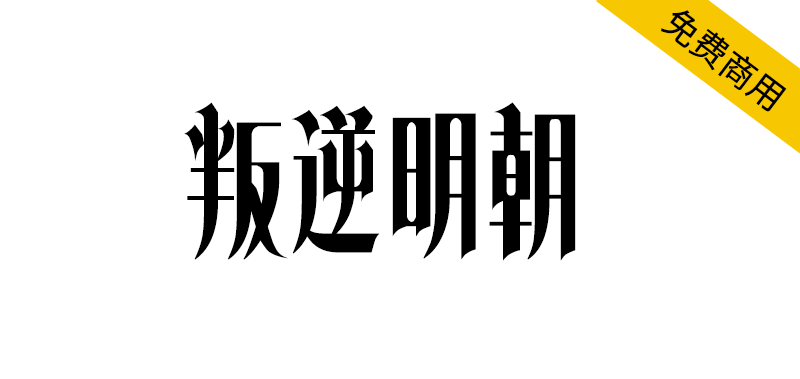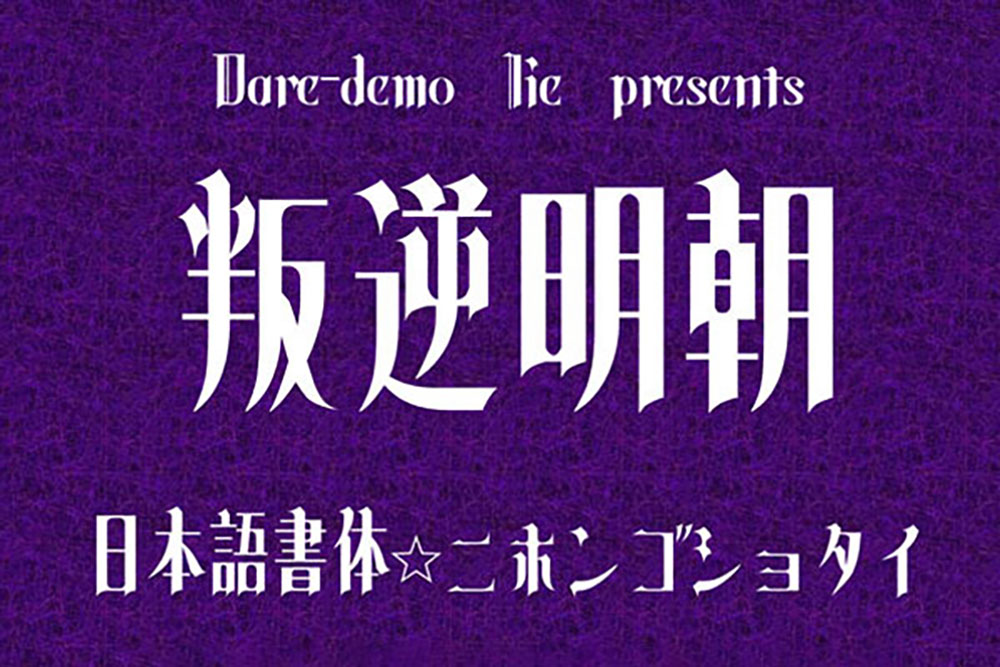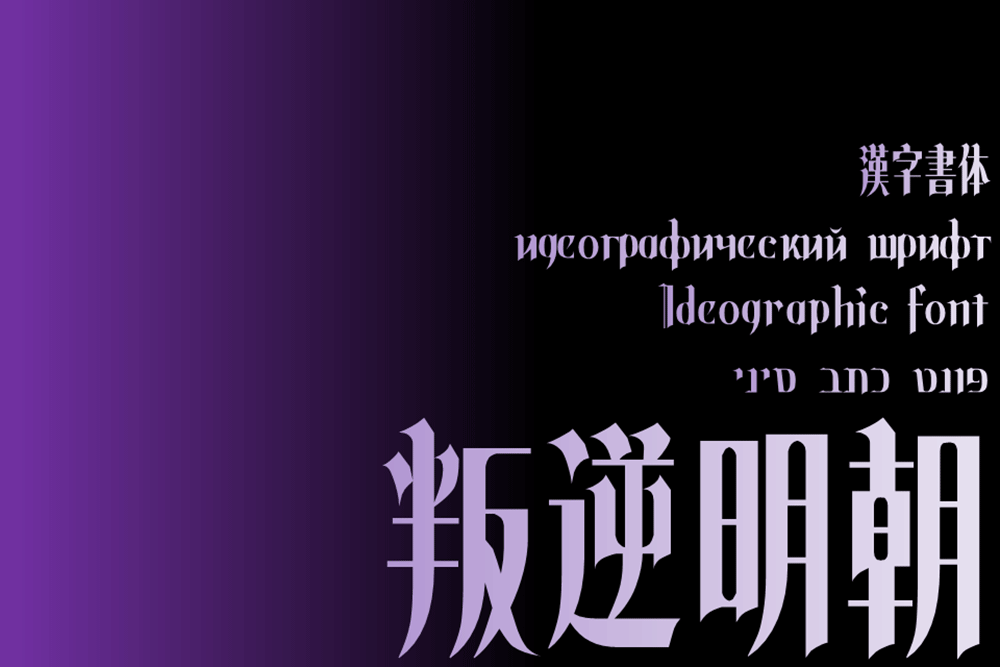
【叛逆明朝】一款设计感很强烈的免费哥特式风格字体
叛逆明朝(Hangyaku Font)是一款开源免费字体,由日本设计师daredemotypo创作,设计风格大胆独特。Hangyaku这个词在日语中的意思是“反叛”,因此这个字体的名称也代表了设计师的反传统和创新的态度。(注:这款字体适用于日文,目前繁体简体都缺字严重)
叛逆明朝采用了哥特式的设计风格,同时又融合了一些传统字体的元素,使其看起来更加独特。其字形轮廓非常简洁,线条流畅而有力,让整个字体看起来非常清晰易读。设计感强烈,它能够帮助设计师在印刷品、网页设计和广告设计等方面展现出独特的风格和个性。